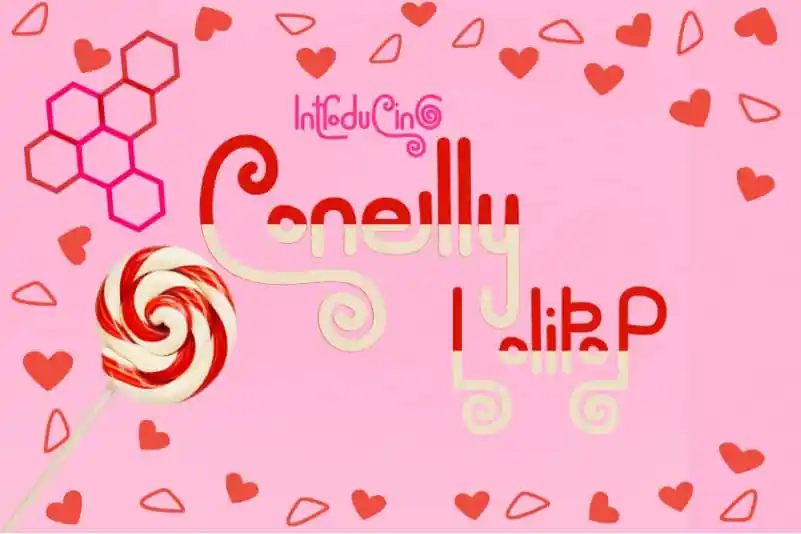
Conelly LolipoP Display Font – Download Grátis
A Conelly LolipoP Display Font é uma excelente escolha para quem busca uma mistura única entre a elegância do calligrafismo tradicional e a contemporaneidade moderna. Esta fonte adora ser usada em variados formatos de trabalho, desde letras para cartões de apresentação até materiais de escritório. É perfeita para aqueles que buscam algo mais original e vibrante no seu design gráfico ou tipográfico. Seja você um designer profissional ou uma pessoa que cria trabalhos como hobby, a Conelly LolipoP Display pode ser a fonte ideal para seus projetos, adicionando um toque único aos textos com sua personalidade peculiar.